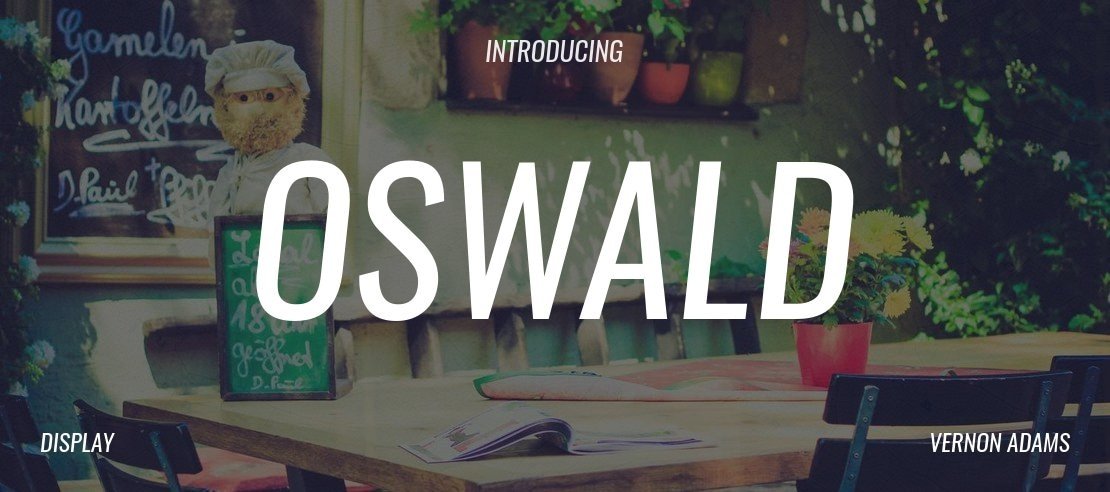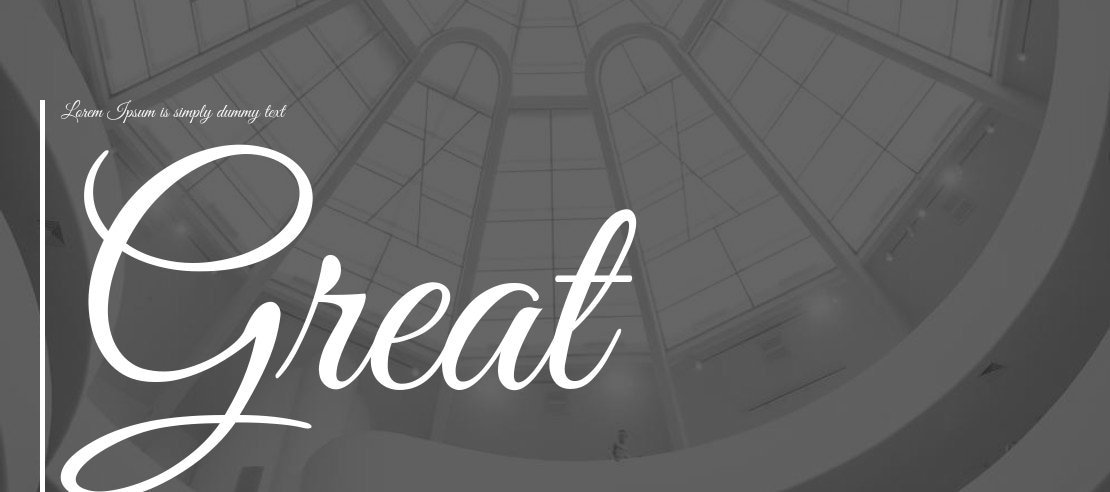
20 Font Keren yang Cocok untuk Desain Kemasan Produk UMKM
Dalam dunia bisnis UMKM, kemasan produk bukan hanya pelindung, tapi juga wajah pertama yang dilihat konsumen. Salah satu elemen penting yang sering diabaikan adalah pemilihan font. Padahal, font bisa membangun kesan elegan, modern, atau playful sesuai karakter brand.
Menurut laporan Nielsen (2024), 60% keputusan konsumen di rak display dipengaruhi oleh desain kemasan, termasuk pemilihan tipografi. Karena itu, memilih font yang tepat sangat penting untuk meningkatkan nilai jual.
Tipografi yang tepat bisa mengubah kemasan sederhana menjadi media komunikasi yang kuat. Bagi UMKM, font bukan hanya soal estetika, tapi juga soal identitas brand.” – Rhino Indonesia
Kenapa Font Penting di Desain Kemasan Produk UMKM?
- Memberi identitas unik pada produk.
- Membantu konsumen mengenali brand dengan cepat.
- Menambah daya tarik visual di antara kompetitor.
- Mendukung branding jangka panjang.
Tips Memilih Font untuk Kemasan Produk
- Pilih font sesuai target pasar (misalnya elegan untuk kosmetik, playful untuk snack anak).
- Pastikan keterbacaan baik meski ukuran teks kecil.
- Kombinasikan font bold untuk headline dan font regular untuk deskripsi.
20 Font Keren untuk Desain Kemasan Produk UMKM
1. Playfair Display
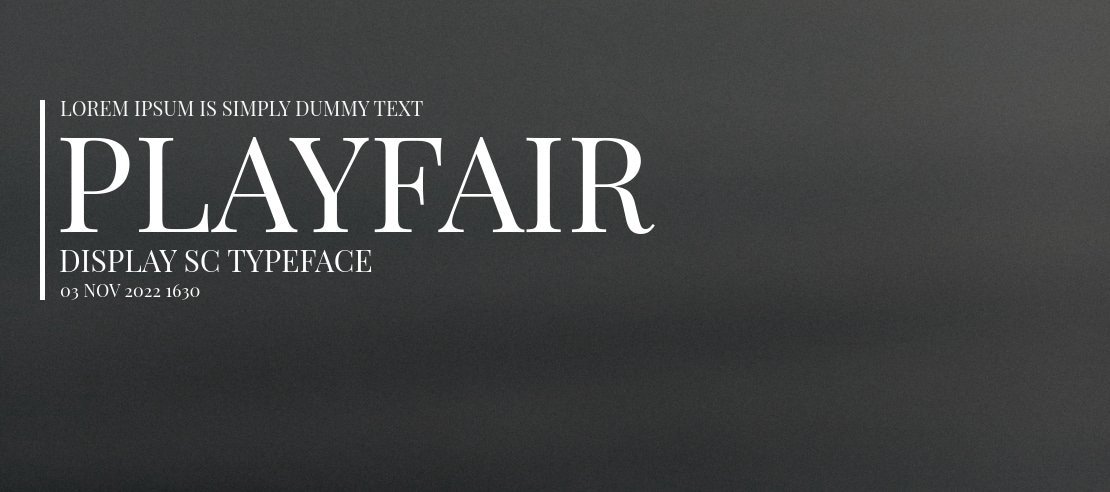
Karakteristik: Serif elegan dengan kontras tinggi.
Kelebihan: Memberikan kesan mewah dan klasik.
Kesan yang Dibawa: Premium, eksklusif, elegan.
Cocok untuk: Produk kosmetik, parfum, atau cokelat premium.
Playfair Display sering dipakai brand mewah karena bentuk serif-nya menonjolkan keanggunan. Pada kemasan produk UMKM, font ini bisa meningkatkan persepsi kualitas.
2. Raleway
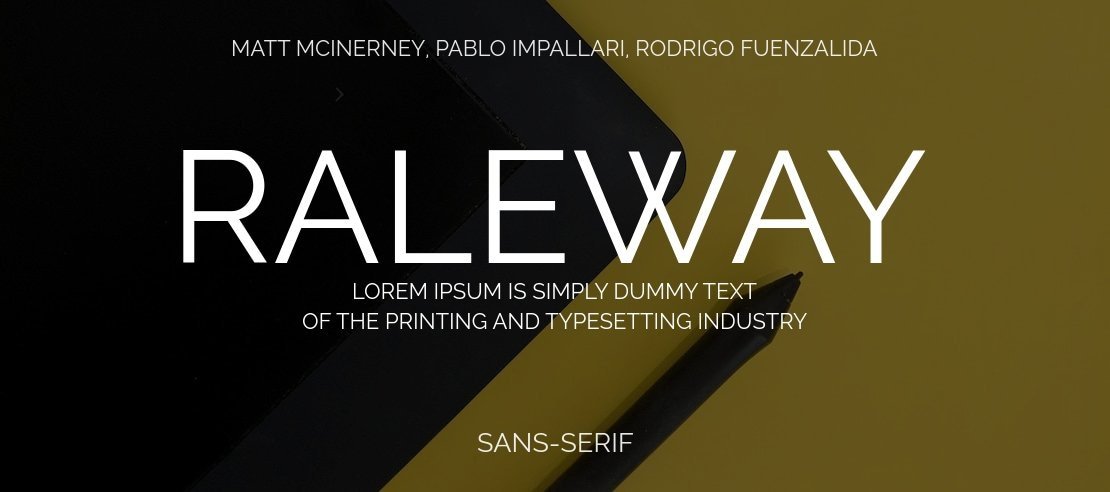
Karakteristik: Geometris, tipis namun modern.
Kelebihan: Terlihat stylish dengan nuansa kontemporer.
Kesan yang Dibawa: Modern, bersih, profesional.
Cocok untuk: Minuman sehat, startup makanan organik.
Raleway cocok untuk UMKM yang ingin tampil segar dan modern, dengan garis halus yang tetap terbaca jelas di kemasan.
3. Montserrat
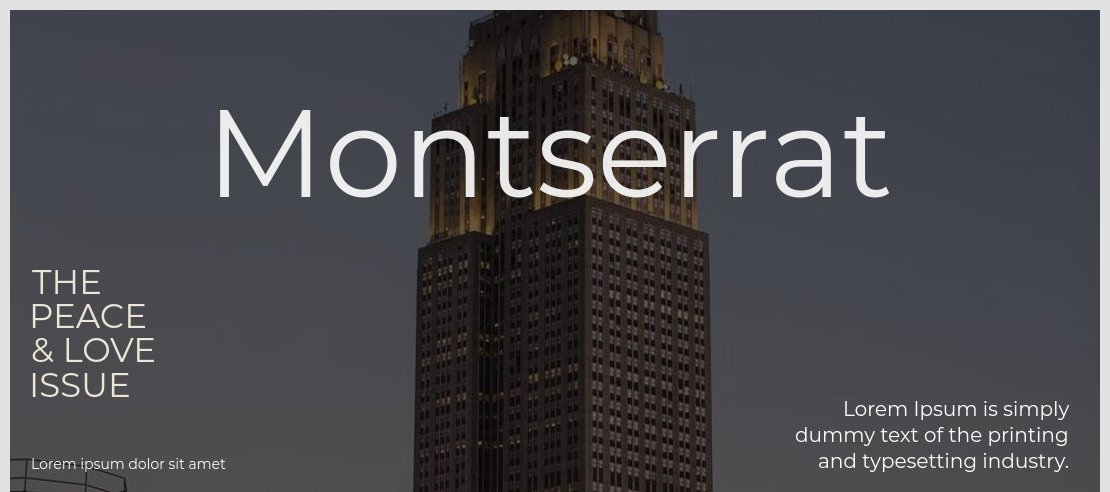
Karakteristik: Sans-serif geometris, tegas.
Kelebihan: Serbaguna dan mudah dibaca di semua ukuran.
Kesan yang Dibawa: Minimalis, urban, modern.
Cocok untuk: Snack kekinian, kopi botolan, fashion retail.
Montserrat menjadi salah satu font paling populer karena fleksibilitasnya, sangat ideal untuk kemasan UMKM dengan target anak muda.
4. Pacifico
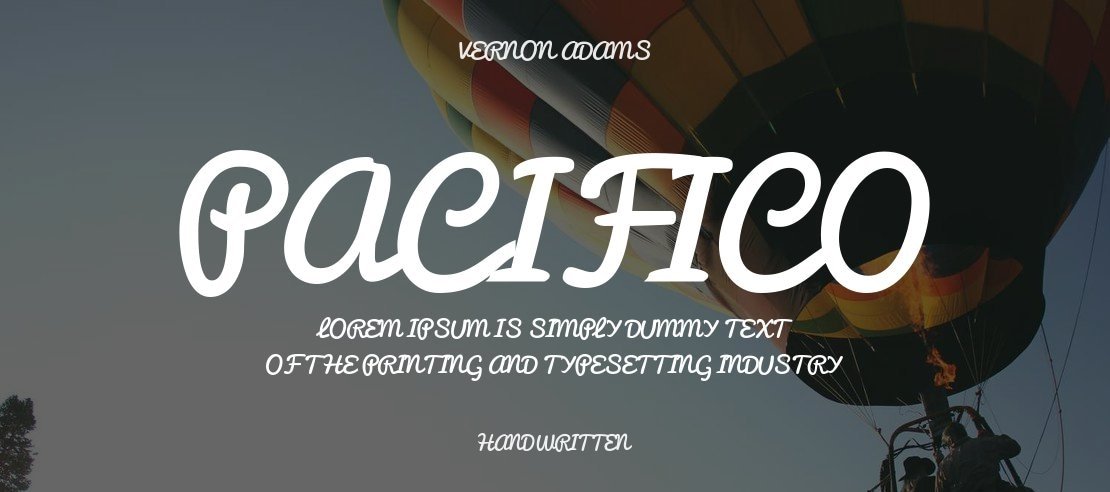
Karakteristik: Script santai dengan goresan lembut.
Kelebihan: Memberikan nuansa ramah dan playful.
Kesan yang Dibawa: Fun, friendly, casual.
Cocok untuk: Bakery, snack anak, minuman manis.
Pacifico menghadirkan suasana hangat, cocok untuk UMKM yang ingin terlihat akrab dan ceria.
5. Lobster
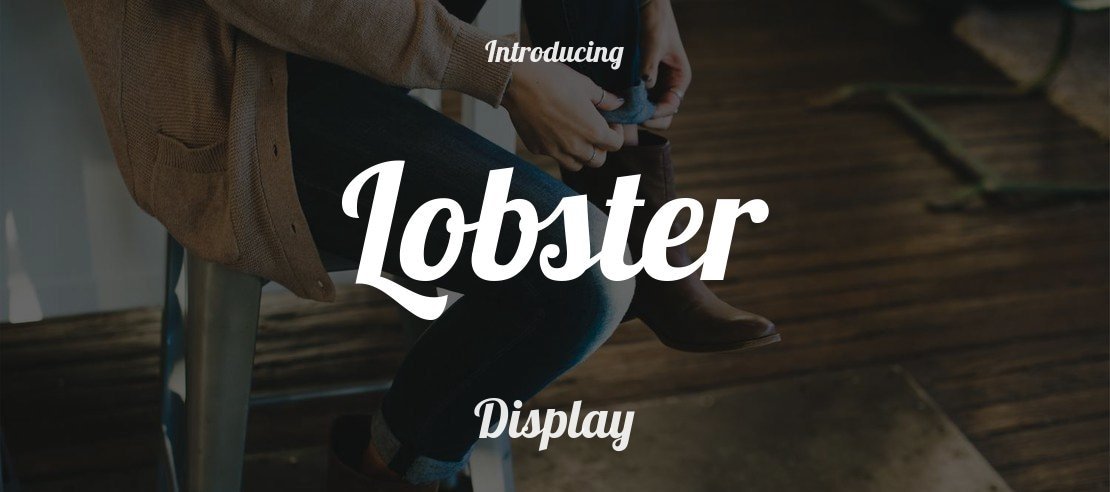
Karakteristik: Script bold dengan karakter unik.
Kelebihan: Sangat mencolok dan mudah dikenali.
Kesan yang Dibawa: Vintage, unik, kreatif.
Cocok untuk: Minuman botol, café, produk handmade.
Lobster sudah ikonik di dunia desain kemasan, banyak dipakai brand minuman karena bentuknya ekspresif.
6. Bebas Neue
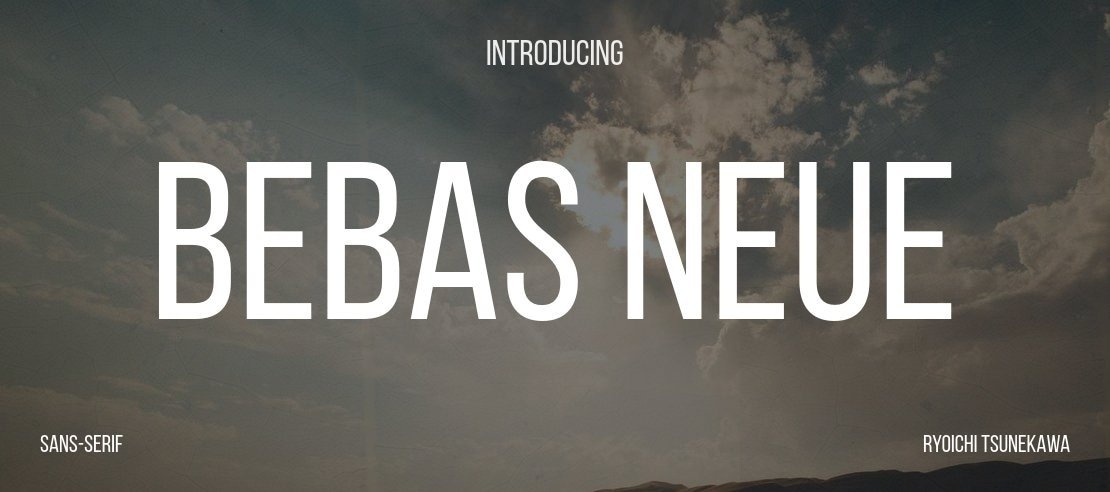
Karakteristik: Sans-serif all caps, bold.
Kelebihan: Gratis dan multifungsi.
Kesan yang Dibawa: Urban, tegas, kontemporer.
Cocok untuk: Snack street food, kemasan makanan ringan.
Bebas Neue punya kekuatan visual yang langsung terlihat menonjol, apalagi untuk teks besar di kemasan.
7. Poppins
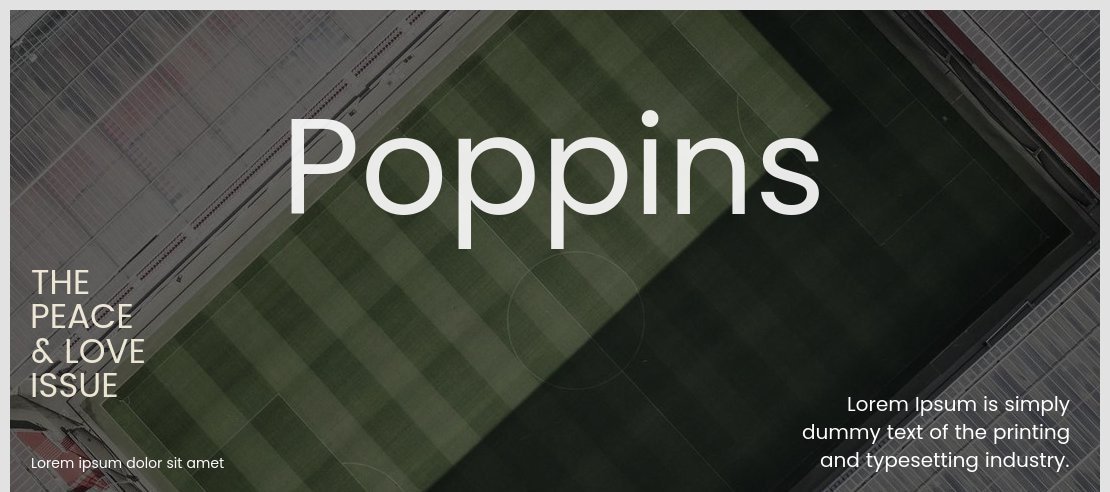
Karakteristik: Geometris bulat, modern.
Kelebihan: Terlihat bersih dan elegan.
Kesan yang Dibawa: Stylish, modern, simpel.
Cocok untuk: Produk teknologi, fashion, dan retail modern.
Poppins sering dipilih UMKM yang ingin memberi sentuhan profesional sekaligus modern di kemasan produknya.
8. Amatic SC
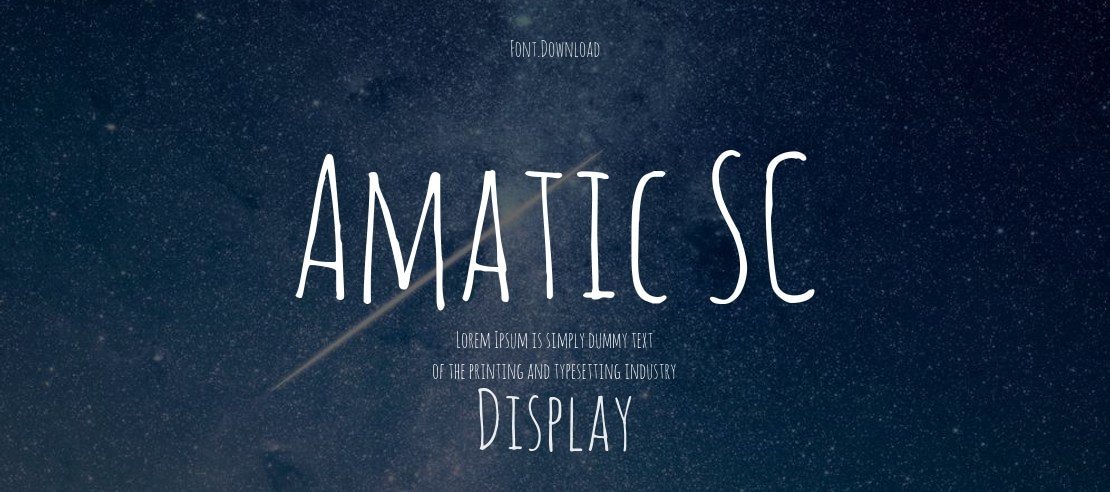
Karakteristik: Handwritten tipis, all caps.
Kelebihan: Memberikan nuansa personal dan alami.